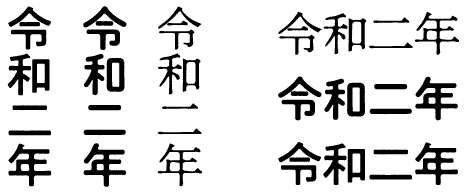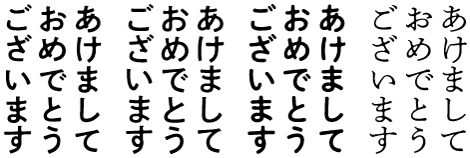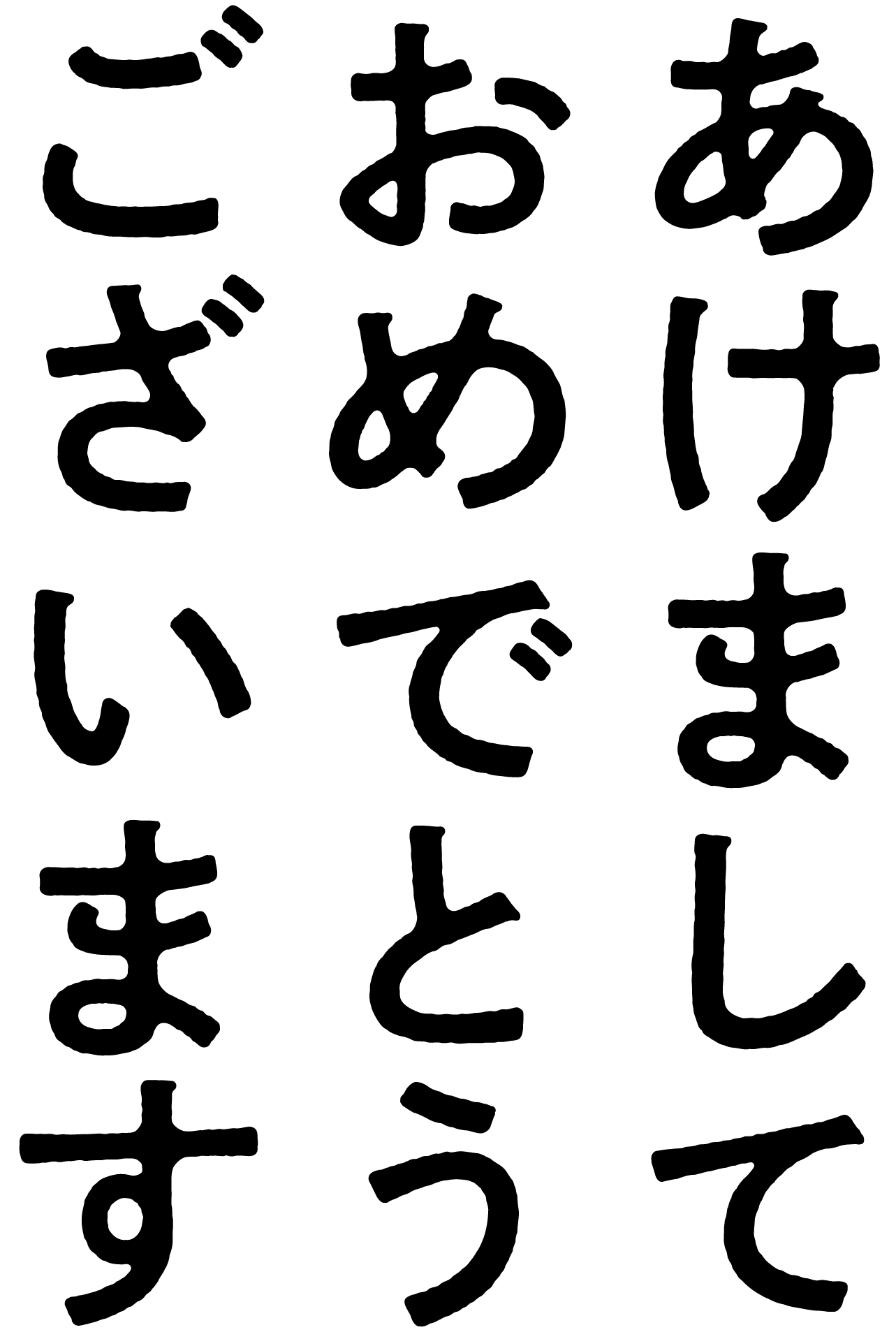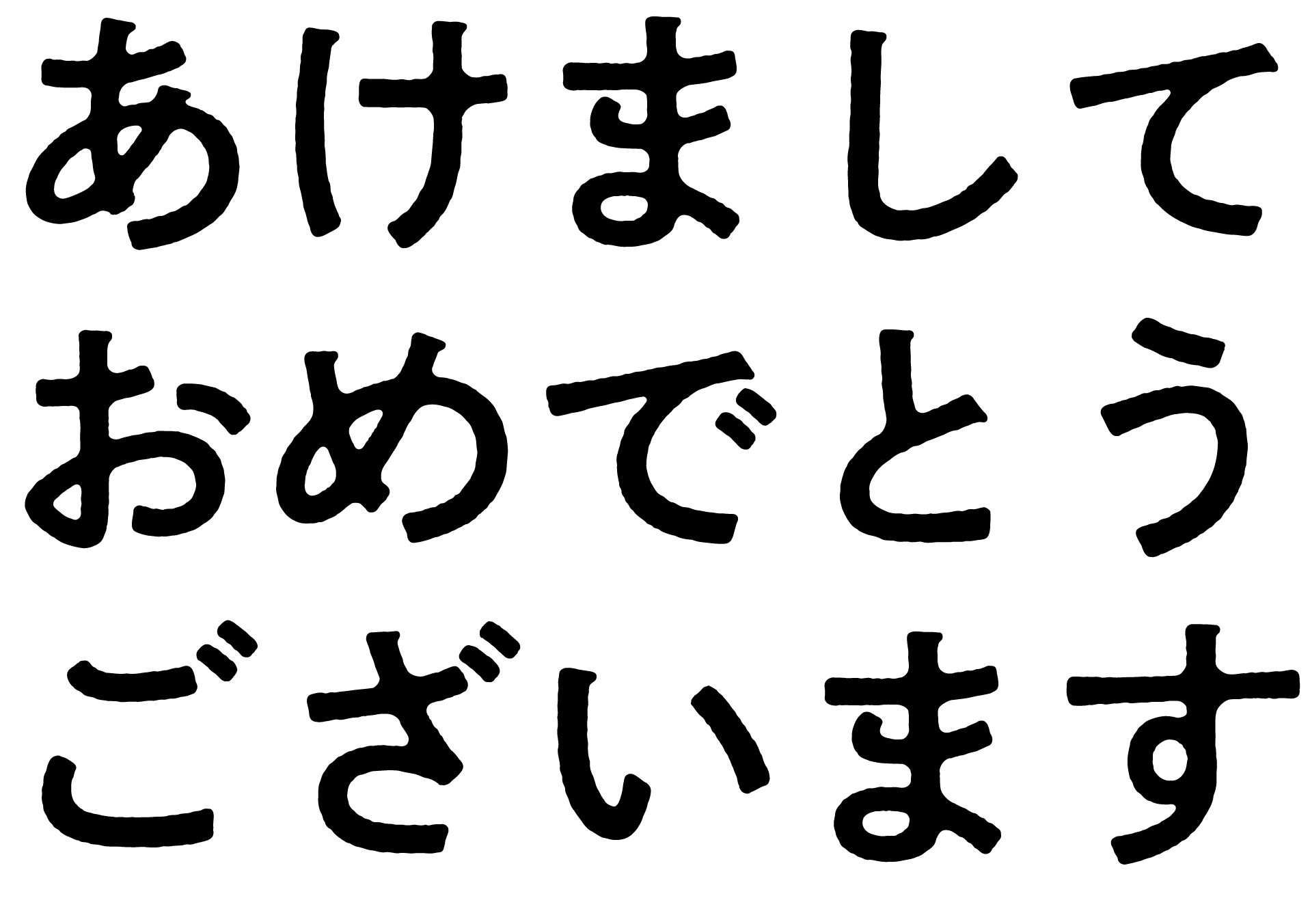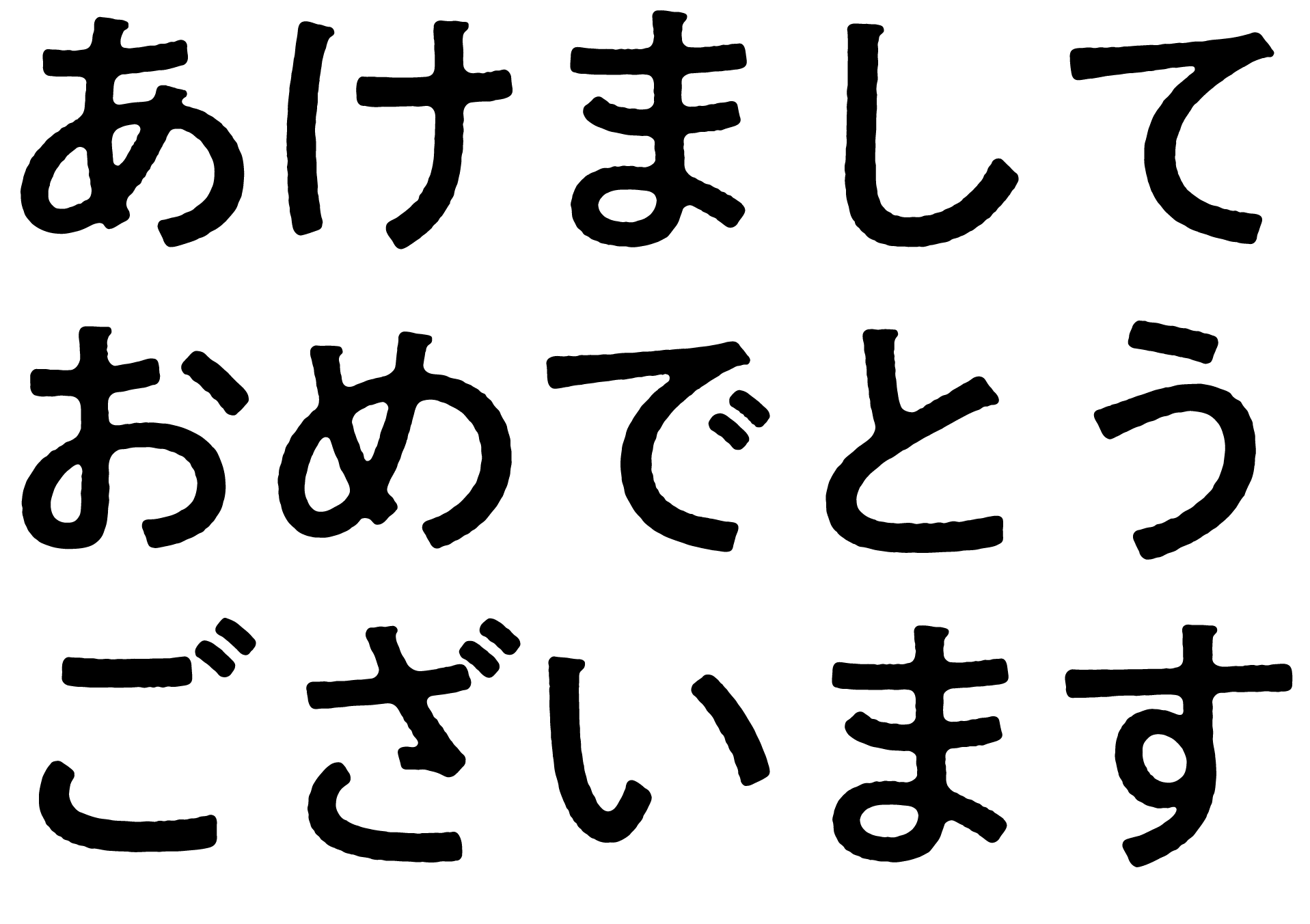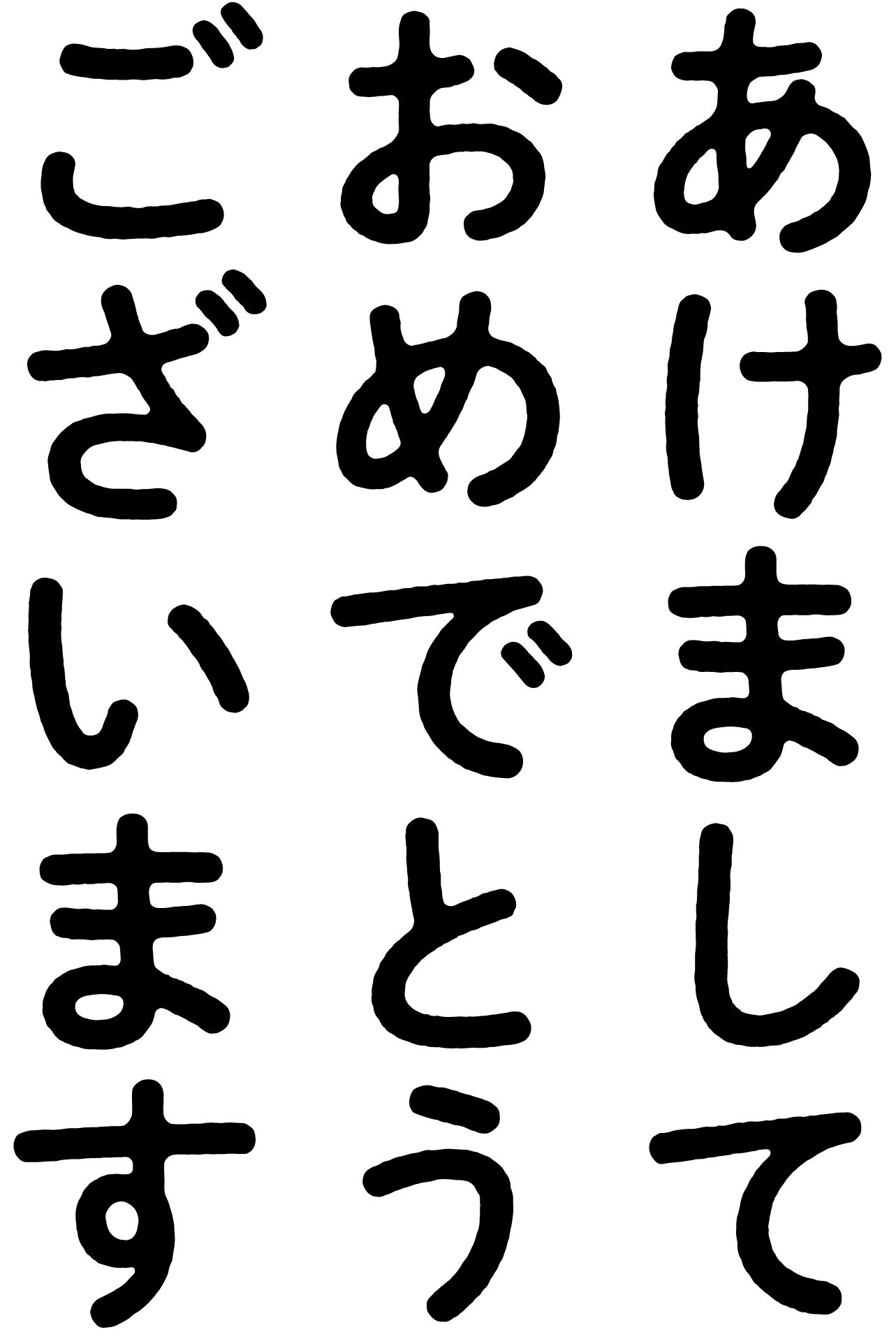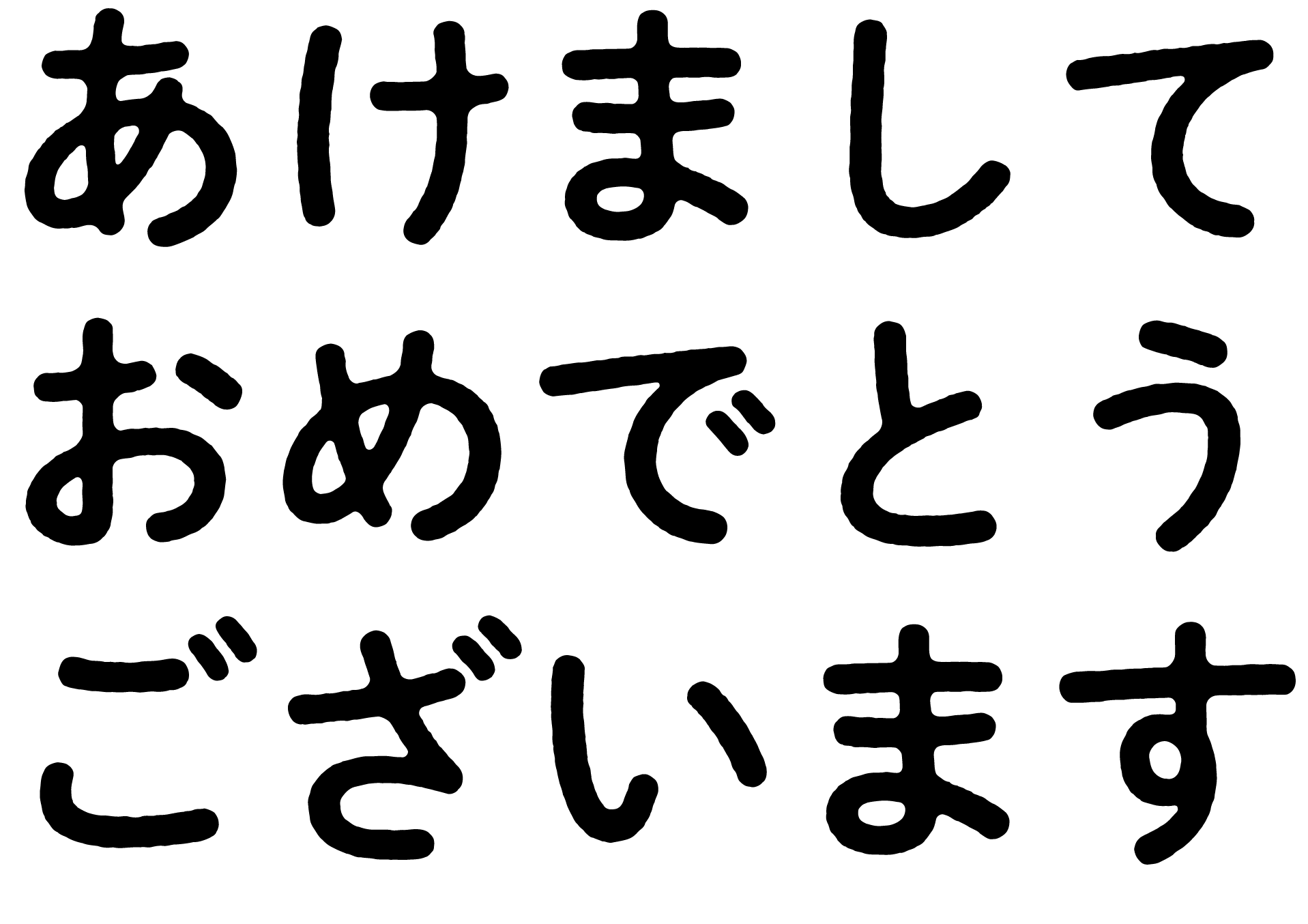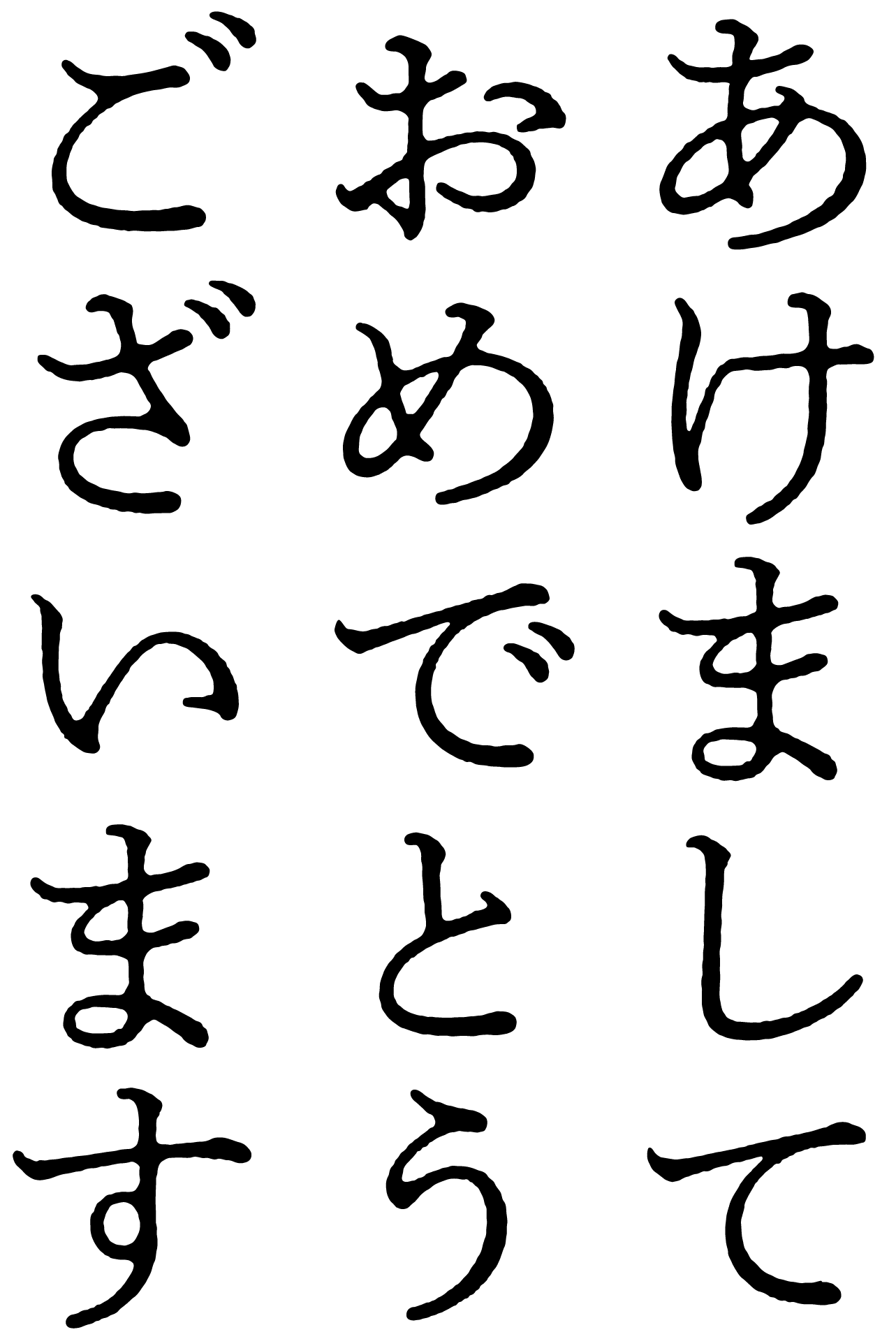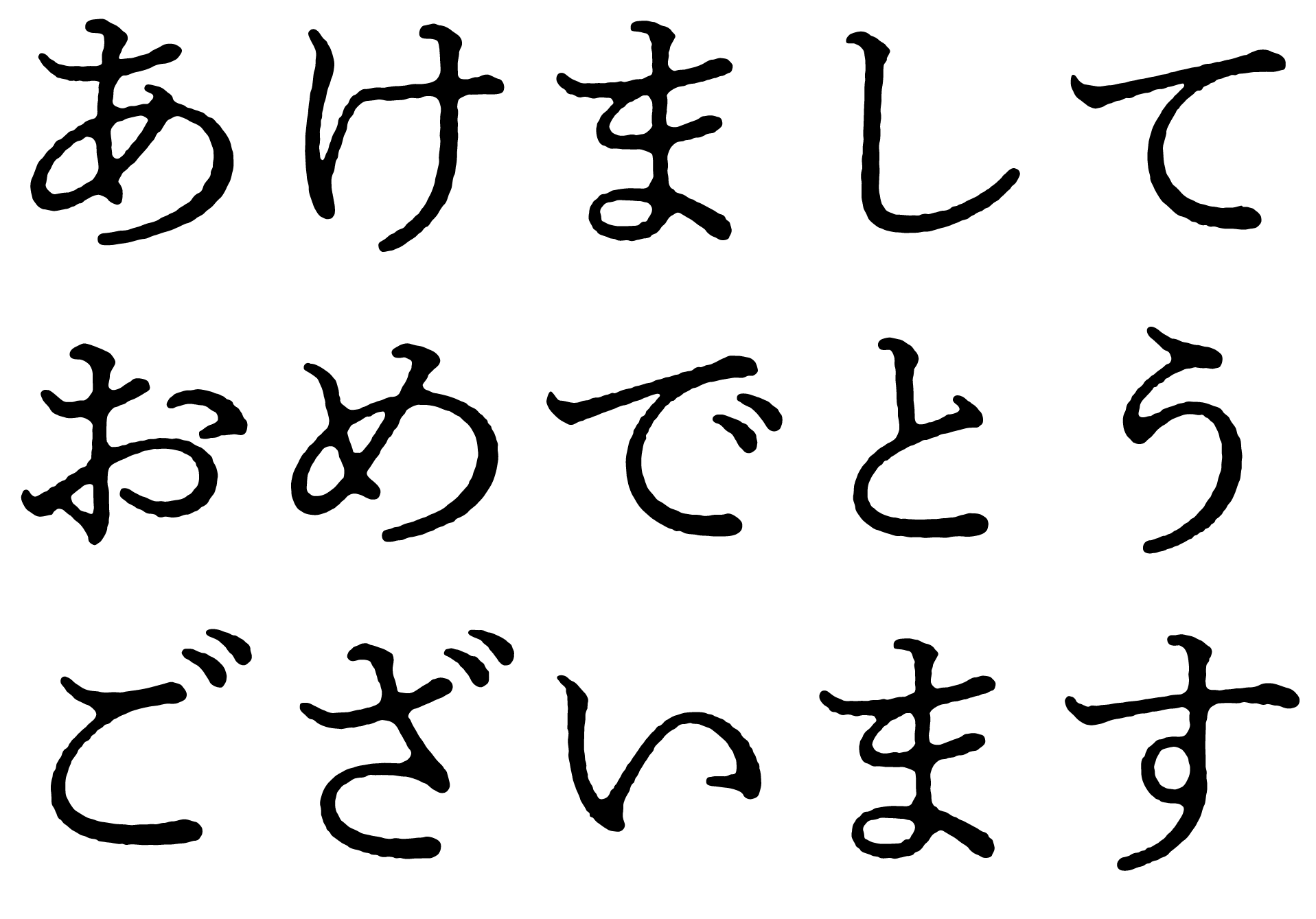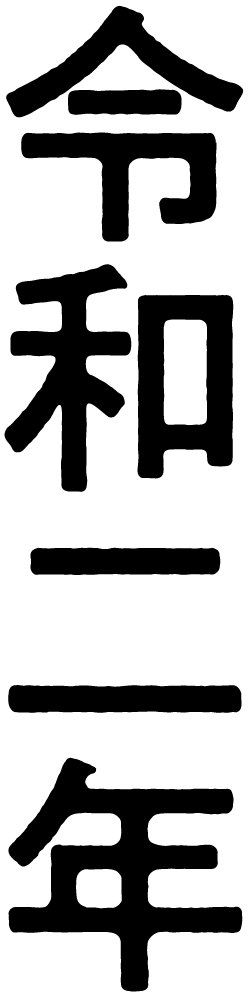
秀英体のコネタ
第43回 2020年も新年の挨拶を秀英体で送ろう!
2019年も残りわずかとなりました。
令和はじめてのお正月、秀英体で新年のご挨拶はいかがでしょうか。
秀英体のフラッグシップ「秀英初号明朝」に、ご好評いただいているにじみシリーズ「秀英にじみ明朝L」「秀英にじみ丸ゴシックB」など6種類のラインナップが揃いました!
やはり新年のご挨拶は年賀状という方には、これまでお届けしてきた「秀英体で年賀状」の素材がお役に立てるかもしれません。
- ※来年の干支である「子」は、12年前のこちらから。秀英舎・大日本印刷が誇る最大規模の見本帳、大正3年版『活版見本帖 Type Specimens』から、7種類のかわいいねずみが登場しています。
「令和」を秀英体で!
「平成」から「令和」に元号が変わり、フォントの世界でも変化がありました。日本語フォントには「㍾」「㍽」「㍼」「㍻」といった元号の合字が含まれています。今回の改元に伴い、新たな合字「
」が追加されることになり、秀英体もすべての書体で対応しました。
左から、秀英明朝・秀英初号明朝・秀英角ゴシック・秀英丸ゴシック
しかし、年賀状で合字はあまり出番がなさそう……。ここは今年、明朝、丸ゴシックに続いて、角ゴシックまで揃った秀英体にじみシリーズで「令和」をどうぞ!
右(上)から、秀英にじみ明朝(縦組
,横組
)、秀英にじみ丸ゴシック(縦組
,横組
)、秀英にじみ角ゴシック(縦組
,横組
定番のご挨拶もにじみシリーズで……
右から、秀英にじみ明朝
、
秀英にじみ丸ゴシック
、
秀英にじみ角ゴシック金
、
秀英にじみ角ゴシック銀
右上から時計回りに、秀英にじみ丸ゴシック
、
秀英にじみ角ゴシック銀
、
秀英にじみ角ゴシック金
、
秀英にじみ明朝